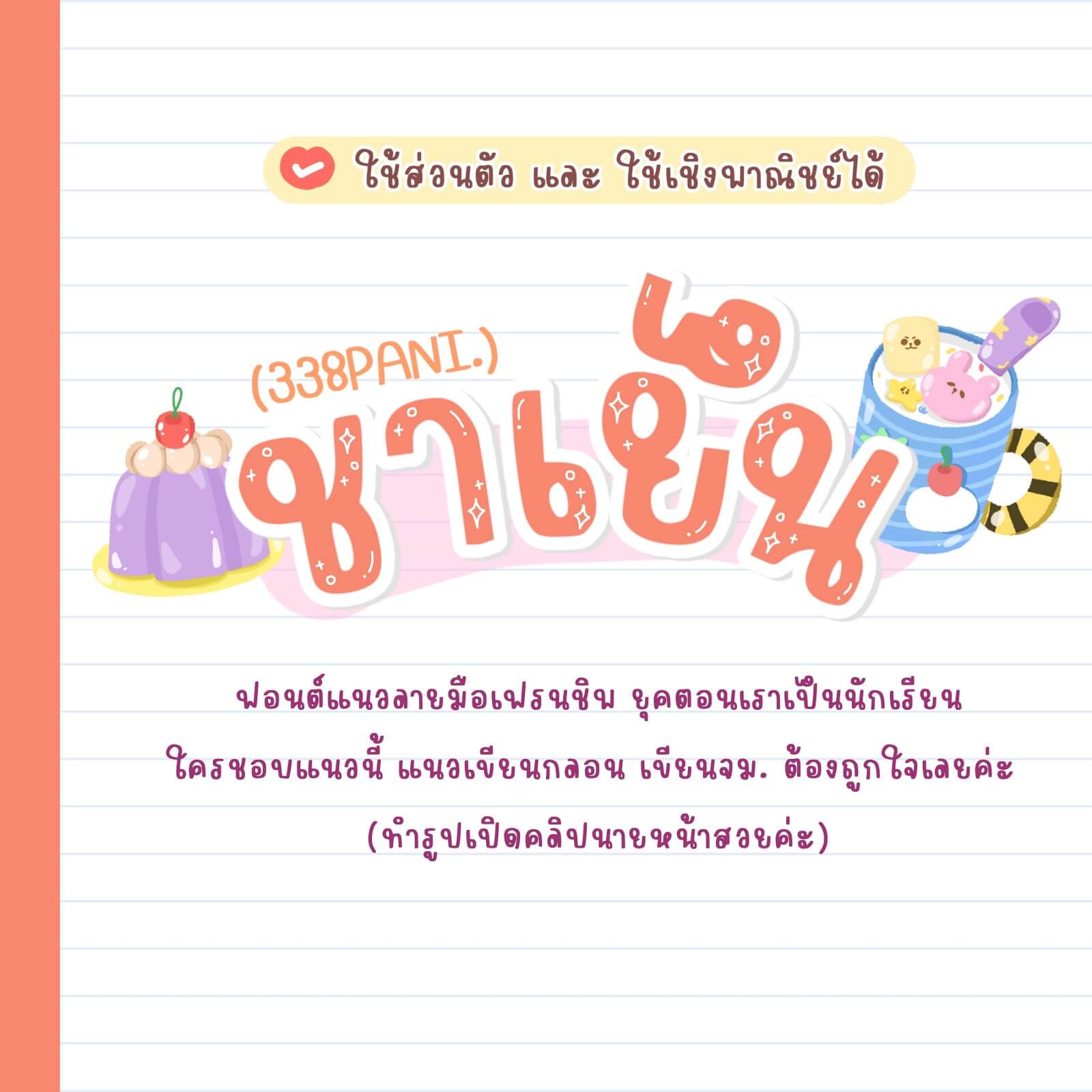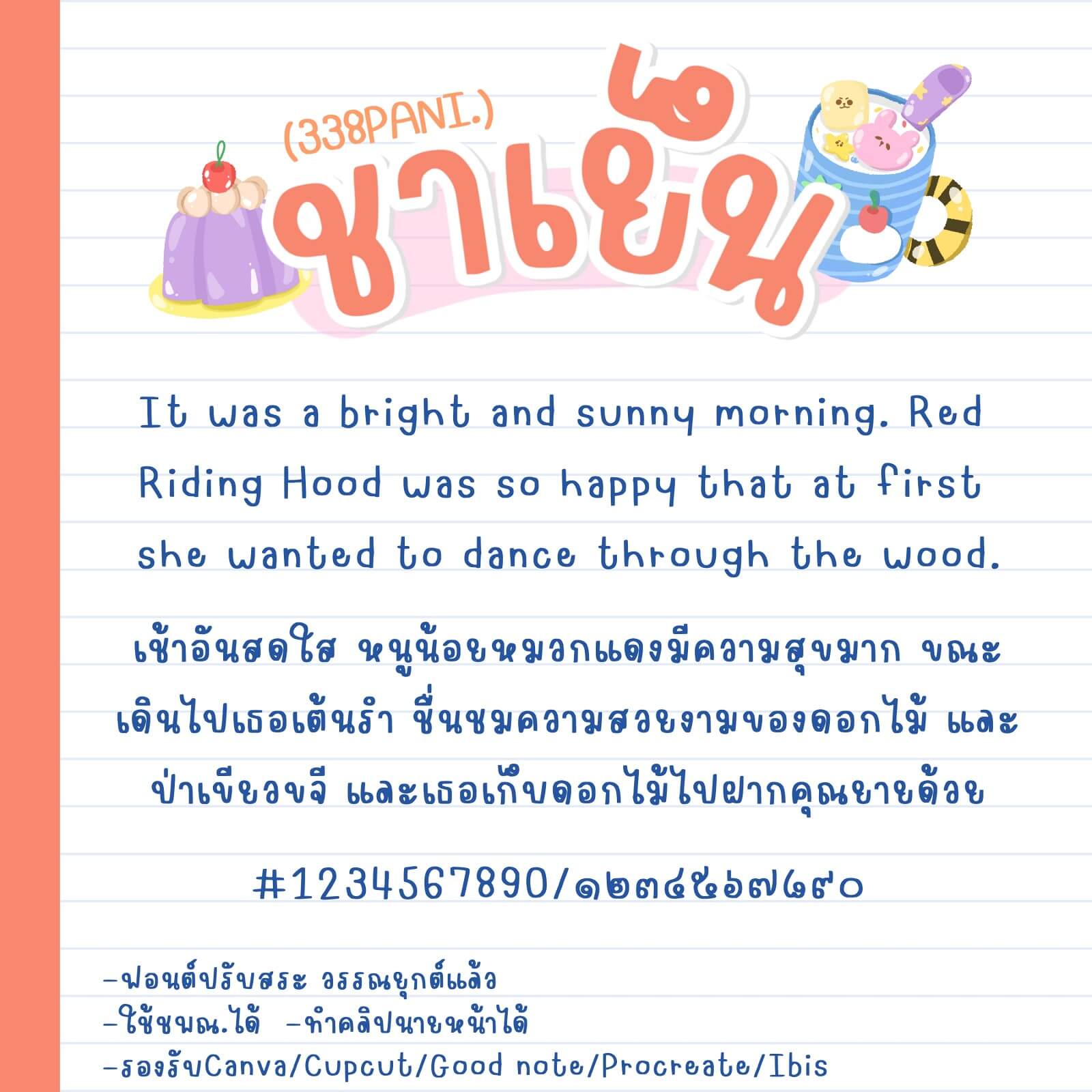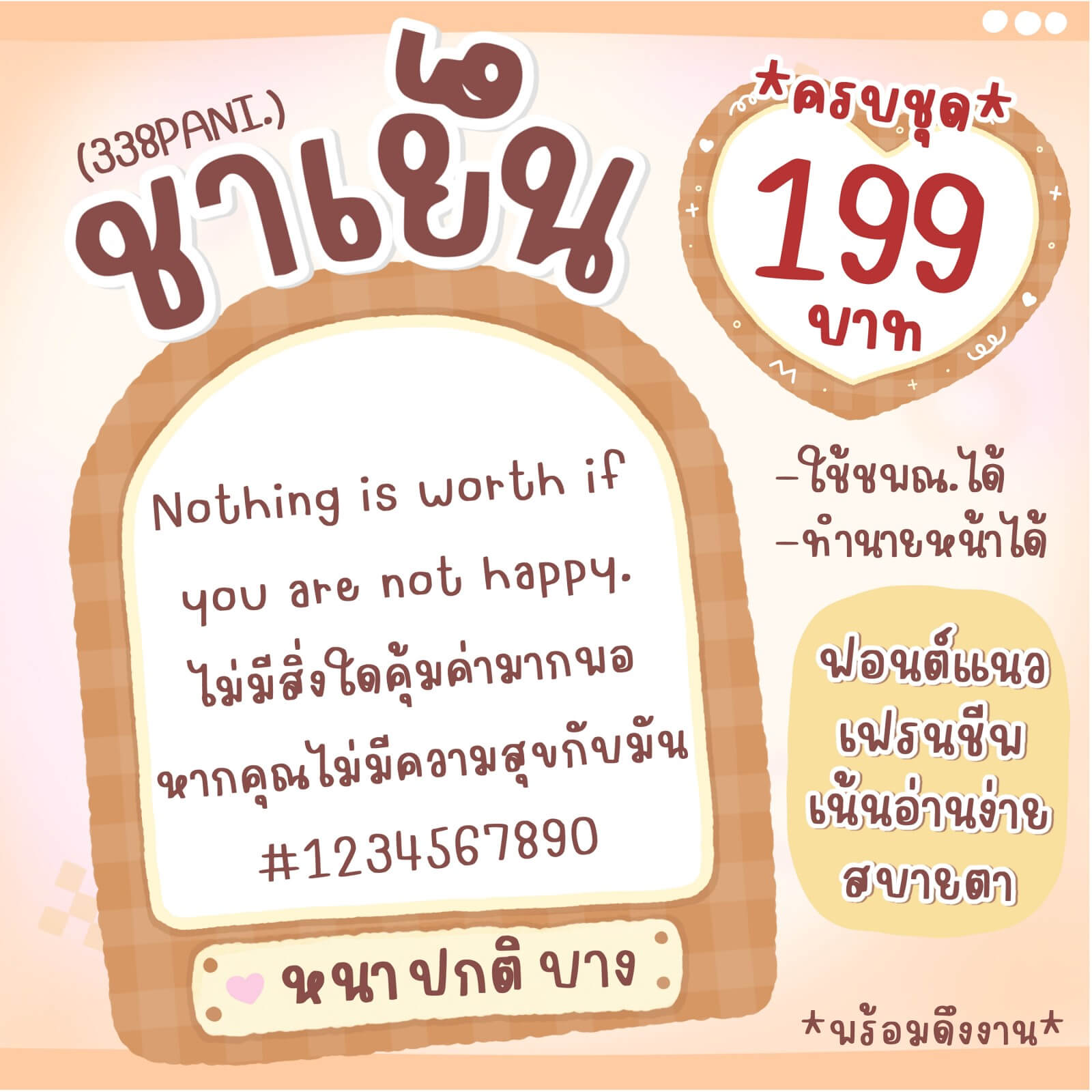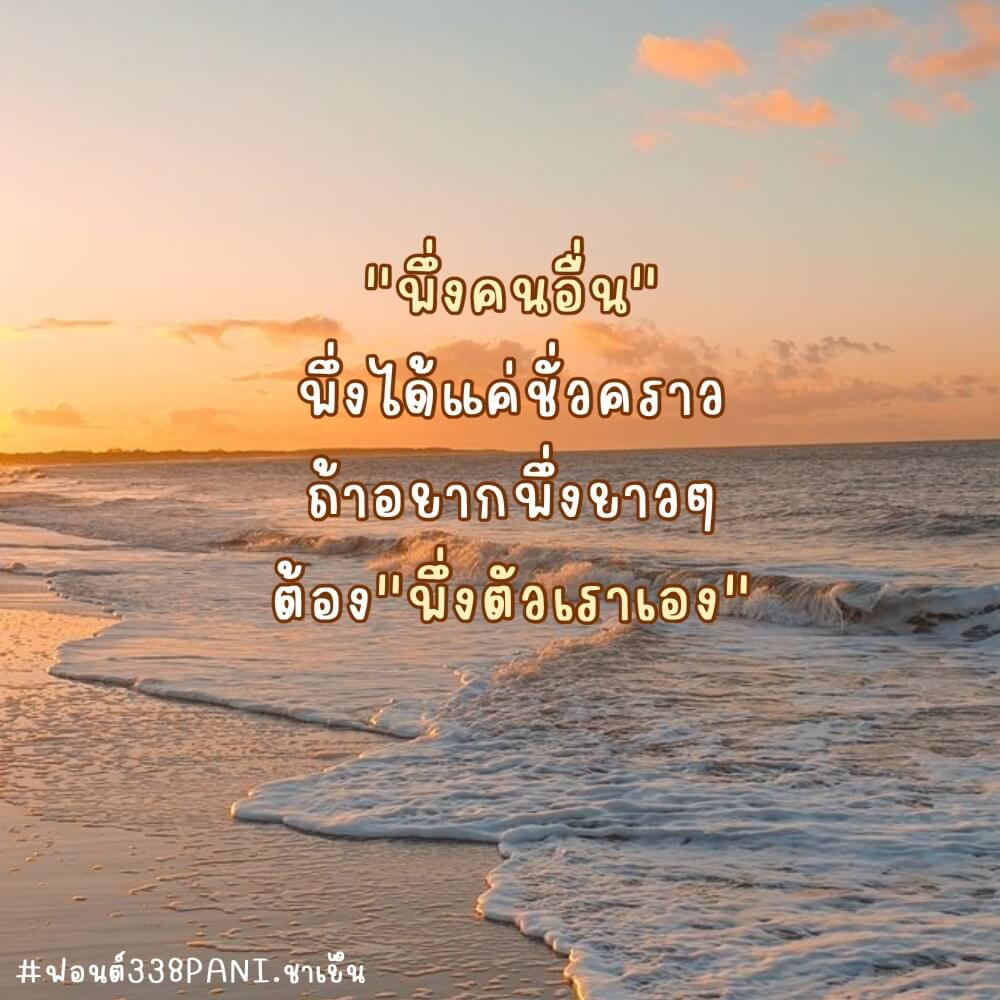
ฟอนต์ 338PANI.ชาเย็น – ฟอนต์แนวลายมือเฟรนด์ชิป ยุคตอนเราเป็นนักเรียน ใครชอบแนวนี้ แนวเขียนกลอน เขียนจดหมาย ต้องถูกใจเลยค่ะ ทำรูปเปิดคลิปนายหน้าได้
338PANI.ชาเย็น